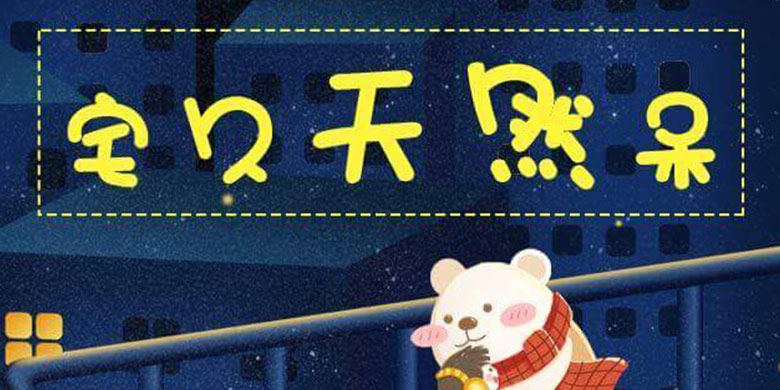
品牌:方正手迹设计师:张明发行时间:2019字库编码:大陆简体(GB2312-80)分类:创意书写字体属性:精品字
该字以夸张的圆形部件作为主要的设计语言,恰到好处的放入到合适的字中,大小部件的对比,使该字具有极强的视觉冲击力,再加上错落有致疏密得当的字体排布。宅久天然呆趣味十足,呆萌新颖。适用于少儿类书刊,及现代诗歌、短文的排版以及文化、商业类品牌的广告语设计。